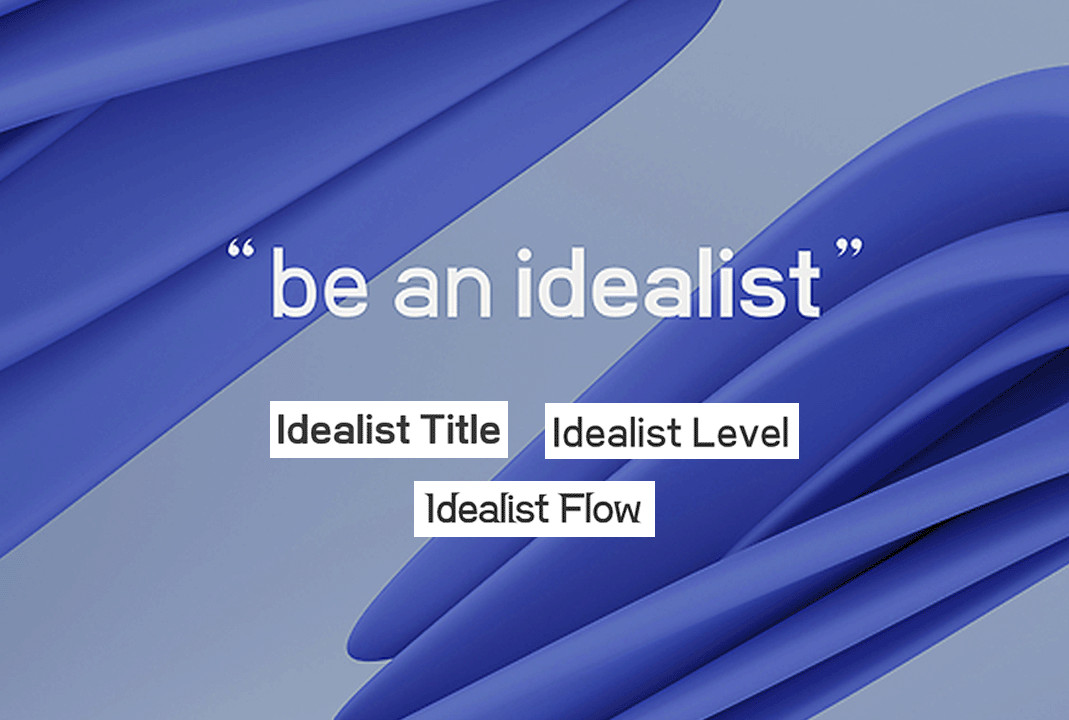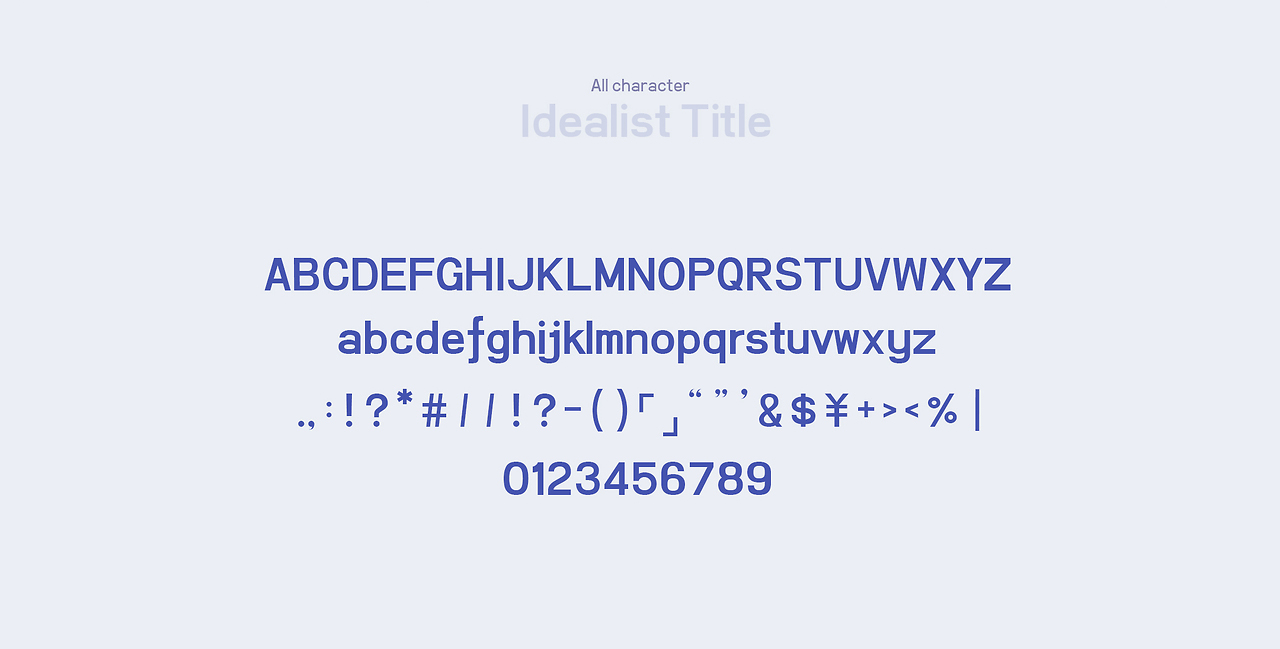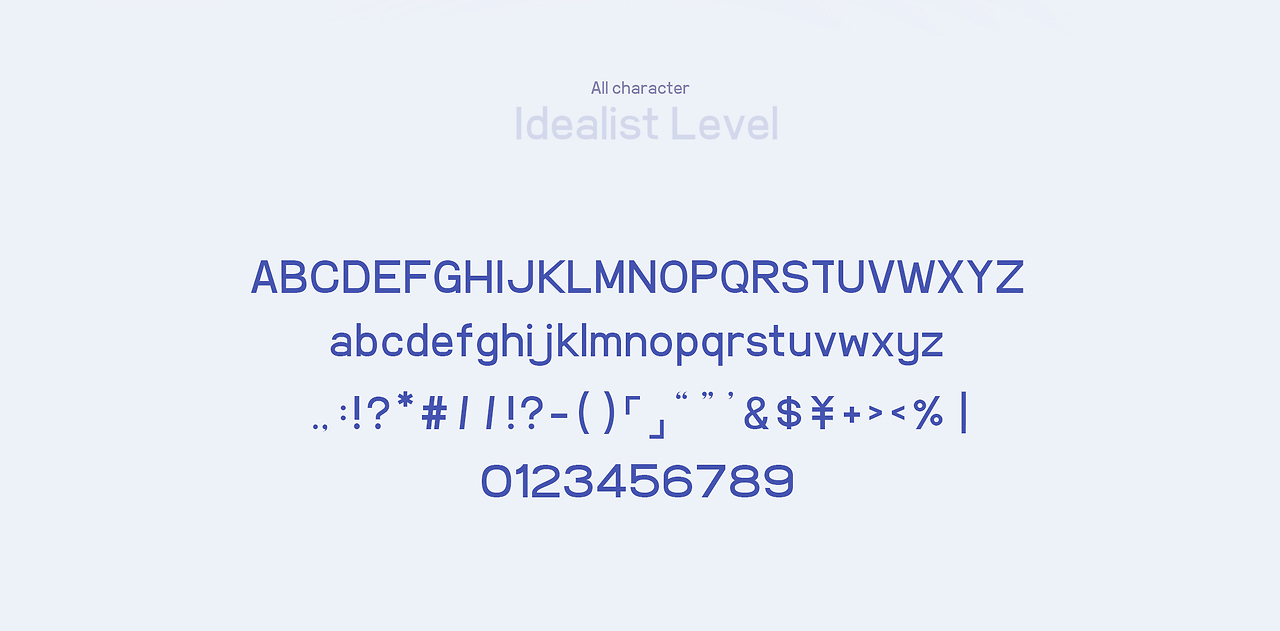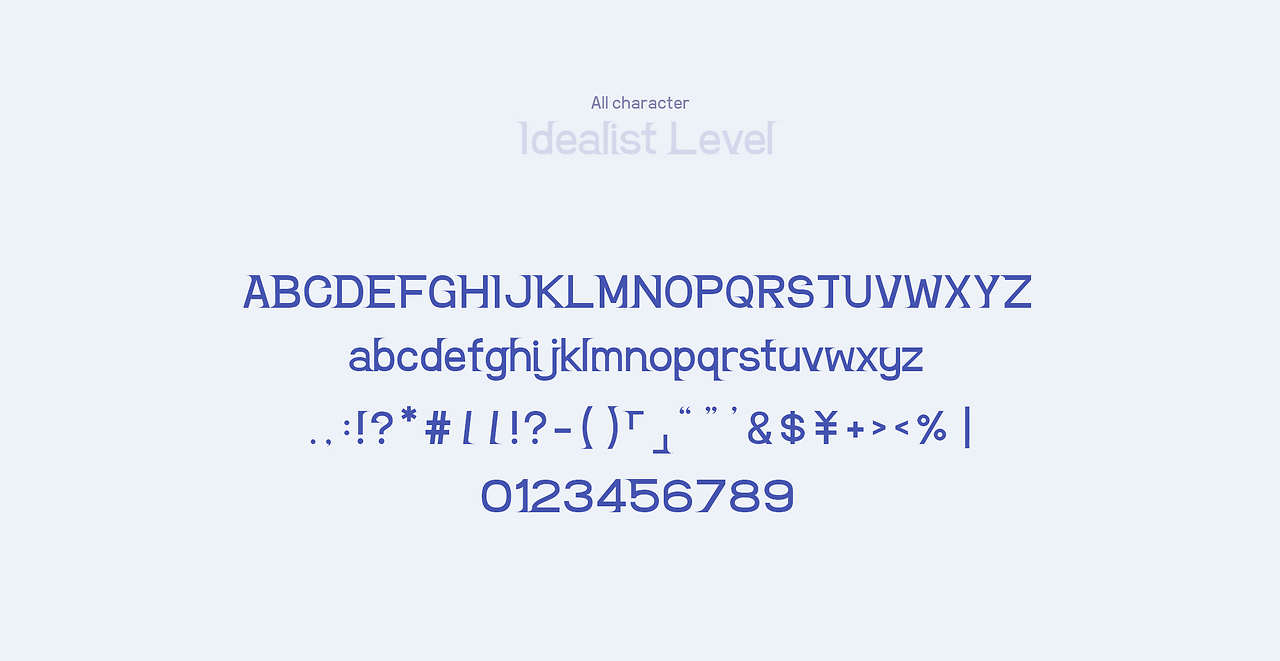
Idealist 系列免费商用英文字库下载
Idealist 是由站酷网友 WallaceWang(uid:Idealist)发布的一款英文字库,该字库包含三款英文字体(Title、Level、Flow)。
字体整体采用几何化的设计理念,特别是在 Idealist Flow 中,字母的转角处理得非常流畅,给人一种动态美感,字体特别适合现代简约风格的品牌设计项目使用。
Idealist Title  适用于标题大字号展示适用
Idealist Level  适用范围较强的字体
Idealist Flow  适用于需文字标题具备较大吸引力时
Idealist Title 字型展示:
Idealist Title  适用于标题大字号展示适用
Idealist Level 字型展示:
Idealist Level  适用范围较强的字体
Idealist Flow 字型展示:
Idealist Flow  适用于需文字标题具备较大吸引力时